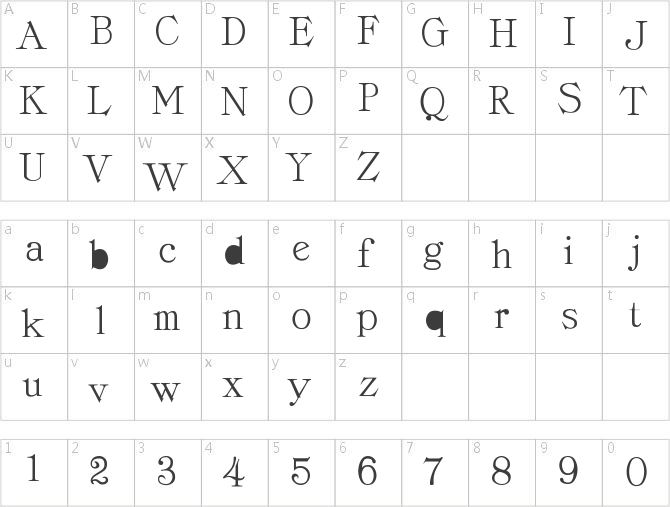
PCCordellaRoman
PCCordellaRoman介绍
PCCordellaRoman字体字库是一款让人赏心悦目、百看不厌的英文字体,适合各类广告和产品包装设计应用,字体大小0.04MB,格式为ttf字体,上传用户是浪遍塞纳河的,作者/版权方为未知
PCCordellaRoman效果图